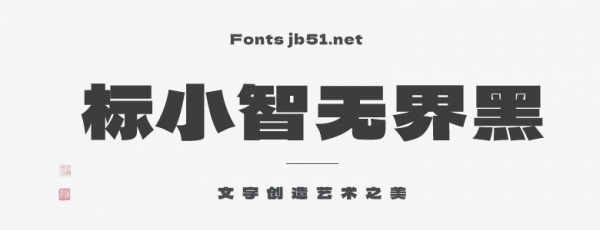
標(biāo)小智無界黑是一款脫胎于日本開源字體——德拉黑體的超粗黑體,標(biāo)小智無界黑按照GB2312-80字體標(biāo)準(zhǔn)來制作,從字庫角度出發(fā),將原字體中的漢字字形更改為更加符合國標(biāo)的字形,在字體細(xì)節(jié)方面做到盡善盡美.
標(biāo)小智無界黑,是由標(biāo)小智LOGO神器攜手貓啃網(wǎng)一起創(chuàng)作設(shè)計(jì)的第一款品牌字體,允許任何個(gè)人和企業(yè)免費(fèi)使用,包括商用用途,無界無限制字如其名,愿為中文免費(fèi)字體生態(tài)添磚加瓦,來一起看看這款非??岬拿赓M(fèi)商用中文字體吧!
標(biāo)小智無界黑字體結(jié)構(gòu)扁平,筆畫非常粗厚,同時(shí)帶有明顯的尖字體表現(xiàn)出非常高的穩(wěn)定性和強(qiáng)有力的視覺表現(xiàn),非常適合用于logo設(shè)計(jì)、標(biāo)題、海報(bào)和包裝等場合。